Deutscher Prototypograf, Kalligraph, Verleger und Buchhändler. Meisterschüler von Johannes Gutenberg (um 1400–1468) und Lehrer von Arnold Pannartz (o.A.–1476), Conrad Sweynheym (o.A.–um 1474/1477) und Nicolas Jenson (um 1420–1480). Peter Schöffer ist der zweite Typograf nach Gutenberg. Er gilt als der Wegbereiter des verfeinerten Schriftgusses für Buchschriften in Lesesgrößen. Alternative Schreibweisen seines Namens: Peter und Petrus bzw. Scheffer, Schoffer, Schoifher, Schoyfer oder »Petrus Schoeffer de Gernsheim« und »Petrus Gernsheimensis«. 1)
Peter Schöffer wurde zwischen 1420 und 1430 in Gernsheim, einer kleinen Stadt am östlichen Ufer des Reihns in der großherzoglichen hessischen Provinz Starkenburg geboren. Aus Schöffers Jugend ist nur wenig Konkretes 2) überliefert, doch scheint seine außerordentliche künstlerische Begabung, verbunden mit hohen intellektuellen Fähigkeiten, früh erkannt und vor allem vom benediktinischen Klerus ausgebildet worden zu sein. Auch soll der wohlhabende Mainzer Kaufherr und Advokat Johann Fust (um 1400–1466) bereits sehr früh sein väterlicher Gönner und Mentor gewesen sein.
Zwischen 1444 und 1448 war Schöffer an der Universität Erfurt immatrikuliert, wo er Theologie und Jurisprudenz studierte; danach war »Petrus de Gernsheim alias Moguntia« 1449 als Schreiber und Kalligraph (siehe Kalligraphie) an der Sorbonne in Paris tätig, wie im Kolophon einer Handschrift nachzulesen ist; ab 1452 arbeitete er in Mainz mit Johannes Gutenberg zusammen, dessen Meisterschüler und späterer »Erzrivale« er wurde.
Wenngleich Schöffer die Buchdruckerkunst nicht erfunden hat, so war er doch rasch ein Meister in diesem neuen Metier und Urheber von technischen und formalen Verbesserungen an den Lettern. Dazu vermerkte der Benediktinerabt und Humanist Johannes Trithemius (1462–1516) in seinem »Catalogus illustrium virorum Germaniae« von 1491:
»Der erwähnte Schöffer, ein kluger, gedankenreicher Kopf, dachte eine leichtere Art aus, Buchstaben zu gießen, und brachte die Kunst zur heutigen Vollendung.«
Als versierter Kalligraph wußte er die hohe Schriftästhetik der mittelalterlichen Manuskripte mit einem praktikablen Inventar an Abbreviaturen und Ligaturen aus der zeitgenössischen Textura zu verbinden und gekonnt in die Typografie der Inkunabeln zu transponieren; so hatte er wesentlichen Anteil am Entstehungsprozeß des Typenrepertoires zur Gutenberg-Bibel (B42), insbesondere an der variantenreichen Ausbildung des Systems der Anschlußbuchstaben.
1455 spielte Schöffer als Zeuge im Prozeß Fust contra Gutenberg eine wohl schicksalhafte Rolle und war nach Gutenbergs fatalem Abgang bis 1466 Werkstattleiter der prosperierenden Gemeinschaftsoffizin im Mainzer Humbrechthaus (siehe Gutenberg und Fust).
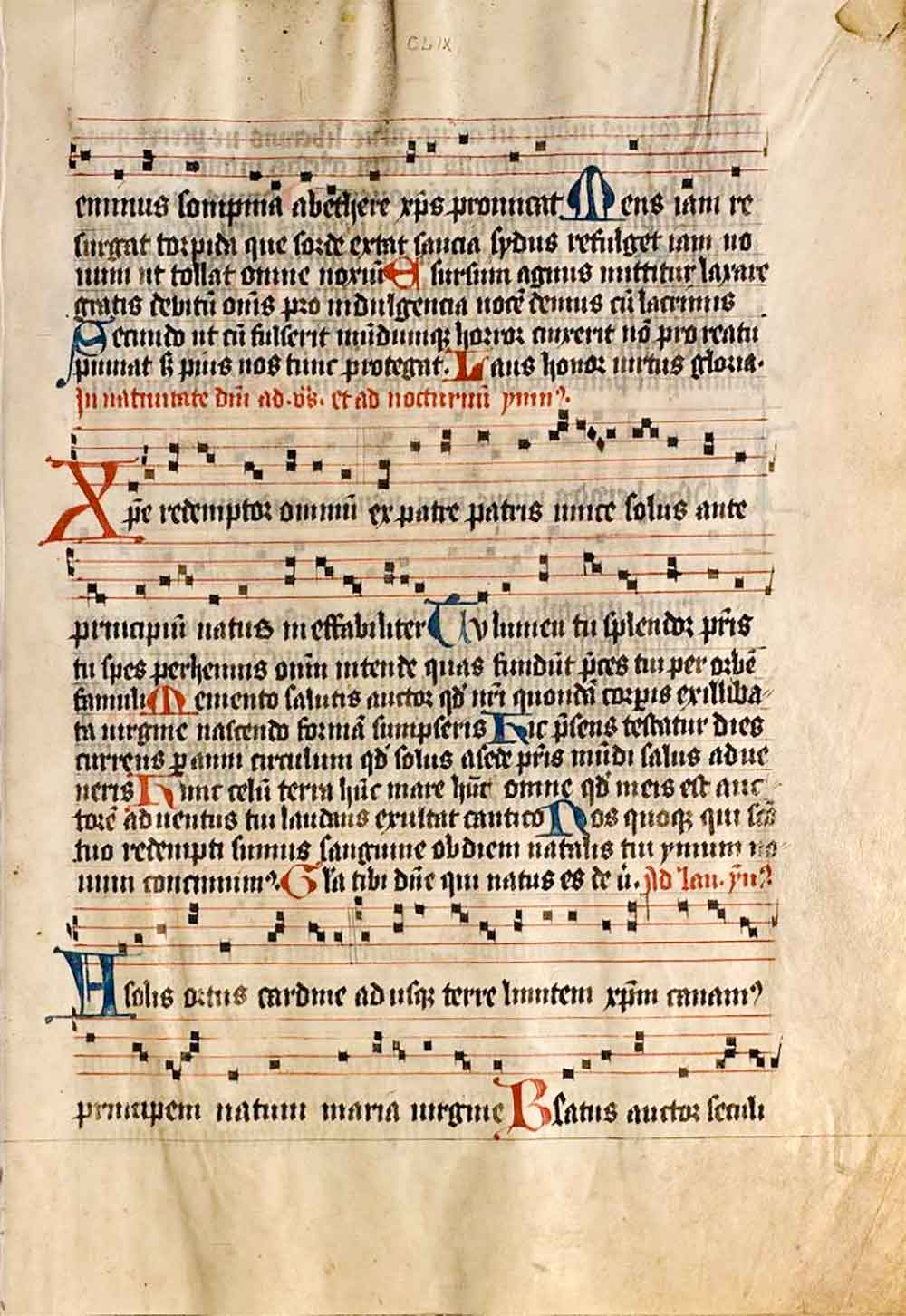
Hier vollendete er am 14. August 1457 das »Psalterium Moguntinum«, die erste datierte Inkunabel der Schriftgeschichte. Der »Mainzer Psalter« umfaßt zwar nur 175 Blatt, ist jedoch mit seinen mehr als 520 verschiedenen Typen, die der traditionellen Missal-Textura liturgischer Handschriften nachgebildet sind, und den erstmals farbig in Königsblau und Kardinalrot gedruckten Lombard-Unzialen einer der satztechnisch aufwändigsten Frühdrucke des 15. Jahrhunderts. Die Analyse zeigt allerdings einen deutlichen Bruch zwischen den ersten und den weiteren Lagen, weshalb die Paläotypie einzelne Psalterteile noch Gutenberg zuschreibt, auch wenn im Kolophon – dem ersten Impressum der abendländischen Typografie – Fust und Schöffer sich dezidiert als Drucker nennen.
Petrus Schöffer hatte neben der für Liturgica verwendeten Psaltertype frühzeitig auch eine Gotico-Antiqua geschaffen, die Elemente der Rotunda mit den Stilmerkmalen der italienischen Humanistenhandschríft verband. Der charakteristisch lichte Satz dieser berühmten »Durandus-Type« war durch die hochgezogenen Oberlängen der Minuskeln b, f, h, k, l, das lange s, ein offenes a und das doppelbäuchige g bedingt. Das am 6. Oktober 1459 publizierte »Rationale divinorum officiorum«, eine von Guilelmus Durandus (Guillelmo Duranti) um 1290 verfaßte allegorische Darstellung der Liturgie, zählt mit seinen kunstreich illuminierten Prunkinitialen zu den schönsten frühen Inkunabeln deutscher Provenienz.
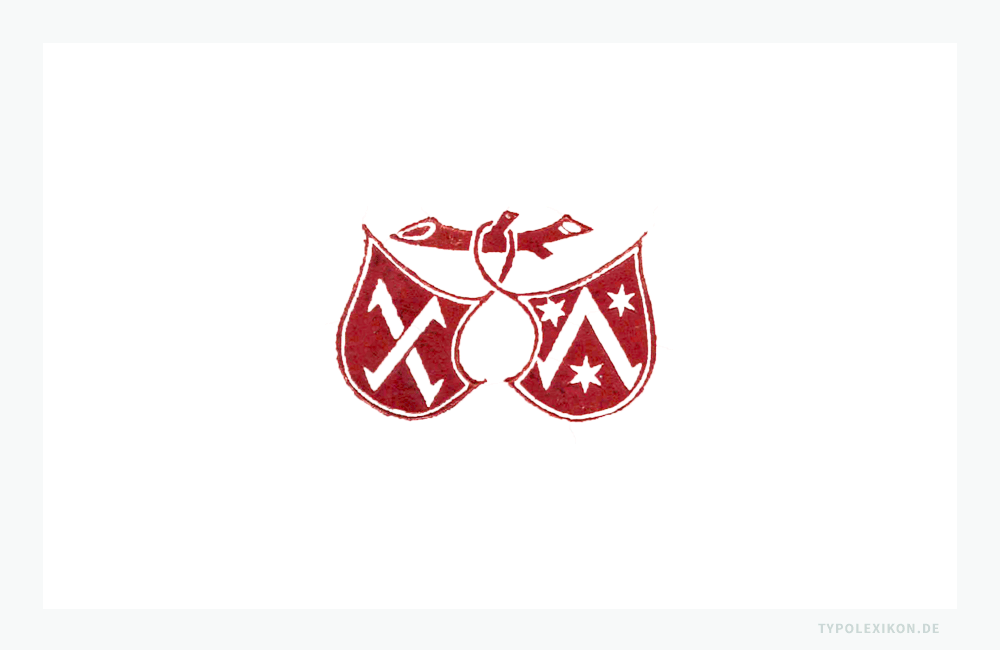
Am 14. August 1462 präsentierte die Fust-Schöffer´sche Offizin mit der 48zeiligen »Biblia latina« ein Meisterwerk, für das Schöffer eine weitere, nun etwas größer dimensionierte Gotico-Antiqua entworfen hatte. In diesem Wiegendruck findet sich auch das älteste europäische Druckersignet: zwei miteinander verbundene, an einem Ast hängende Wappenschilde, die mit stilisierten Winkelhaken und Sternen verziert sind.
Neben solch opulenten liturgischen Prachtinkunabeln, den wichtigsten Standardwerken des kanonischen Rechts, der Theologie und theosophischen Erbauungsliteratur wurden in der Mainzer Gemeinschaftsoffizin aber auch die vielfältigsten Kleindrucke, Akzidenzien, aktuelle amtliche Verlautbarungen sowie gerichtliche Verordnungen und im Zuge der Mainzer Stiftsfehde sogar kirchenpolitische Propagandaschriften – diplomatischerweise für der Erzbischof Diether von Isenburg (1412–1482) und seinen erzbischöflichen Kontrahenten – produziert. Auch die klassische Literatur fehlte selbstverständlich nicht. Eine zweite Edition von Ciceros »De officiis« war das letzte Werk, in dem Fust und Schöffer gemeinsam als Drucker firmierten.
Als Johann Fust 1466 in Paris vermutlich an der Pest verstarb, übernahm Schöffer nicht nur die Offizin, sondern führte auch die bereits ausgedehnten buchhändlerischen Agenden höchst erfolgreich weiter. Anfangs organisierte er den Verkauf seiner Drucke noch über Faktoreien und eigene Bedienstete, die er mit prototypischen Werbeanzeigen ausstattete. Auf einer dieser noch auf lateinisch abgefaßten Reklamen findet sich der originelle Vermerk: »Venditor librorum reperibilis est in hospitio dicto zum Willden mann: Der Buchverkäufer ist in besagtem Wirtshaus Zum wilden Mann anzutreffen.«